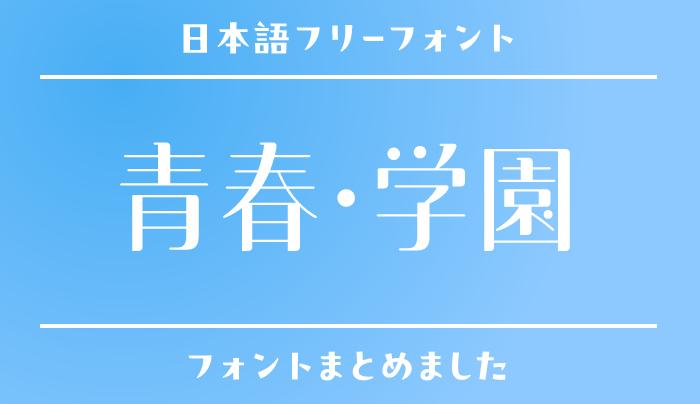
放課後のノート、文化祭のポスター、卒業前に渡す手紙。青春や学園のデザインには、手書きの親密さだけでなく、掲示物らしい明快さや文芸作品らしい静けさも似合います。同じ学校生活でも、どの場面を切り取るかで選びたい文字は変わります。
今回は、フォントラボから青春・学園をテーマに使いたい15書体を紹介します。写真に添える言葉、クラス企画の告知、学校を舞台にした創作まで、具体的な使い道と合わせて選びました。実際の学校名や人名に必要な漢字が入っているかも確認してみてください。
青春・学園を表現する日本語フリーフォント
みかちゃん
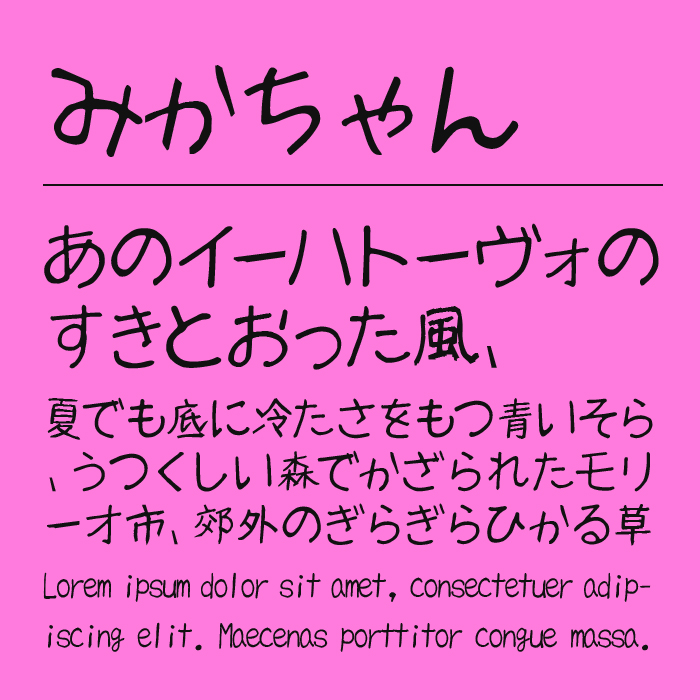
| おすすめの場面 | クラスの思い出写真/寄せ書き風デザイン/卒業記念の一言 |
飾らない筆跡で、友人との距離感を近く。
ほどよく不揃いな文字の大きさや丸みが、友達のノートを読むような親密さを作ります。集合写真に添える一言や、思い出を並べるページにおすすめです。長い案内文まで手書きにせず、話しかけるような言葉だけに使うと効果的。整った本文書体と並べることで、個人の声として見せられます。
ちはや純
| おすすめの場面 | 入学の思い出ページ/素朴な日記風画像/クラス紹介 |
素直な手書きで、少し不器用な気持ちを。
丸みがあり、丁寧に書いたような素朴さを感じる文字です。派手な青春のロゴより、入学した日の記録や初々しい自己紹介などに向いています。余白のある写真に短い感想を添えると、作り込みすぎない表情に。かわいさを装飾で増やすより、言葉を読ませる静かな構成がおすすめです。
きろ字
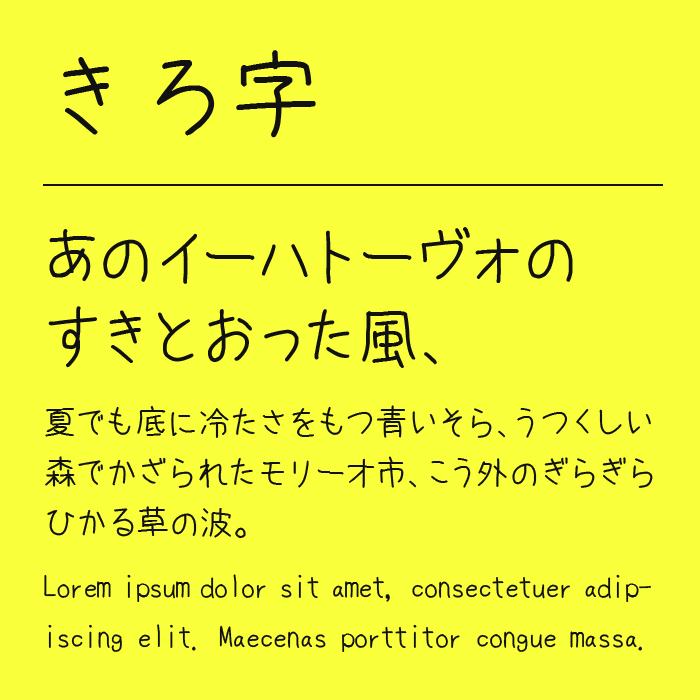
| おすすめの場面 | 文集の短いコメント/部活動の活動記録/交換ノート風レイアウト |
読みやすい手書きで、日常の記録を残す。
手書きらしい温かさを持ちながら、文字の形が落ち着いている書体です。思い出を少し長めに語るコメントや、部活動の記録におすすめ。ラフすぎる文字では読みづらいと感じる場面でも、候補にしやすいバランスです。行間を確保して、文章のかたまりを小さく分けると読み進めやすくなります。
はる手書き
| おすすめの場面 | 卒業前の手紙風コピー/放課後の写真/学園作品のモノローグ |
細い筆跡で、言い切れない余韻を残す。
ノートに書き留めたような細い線が、静かな感情を伝えます。にぎやかな告知より、夕方の教室や帰り道の写真に添える短い言葉と好相性。文章の周りに空間を残すと、控えめな筆跡が活きます。線が細いため、写真に重ねる際は背景との明暗差を確保してください。
ぱぱっとメモ
| おすすめの場面 | ノートの走り書き/学園作品の小道具/部室のメモ風画像 |
整いすぎない文字で、学校生活の一瞬を。
走り書きのような線の揺れが、急いで残したメモの雰囲気を作ります。画面の中心のタイトルより、ノートの片隅や部室の貼り紙にある一言におすすめ。無料のバージョン1は漢字なしなので、かなのメッセージや英数字の予定表示を中心に使うと自然です。漢字を混ぜる場合は見た目の差にも注意しましょう。
まちのてちょう
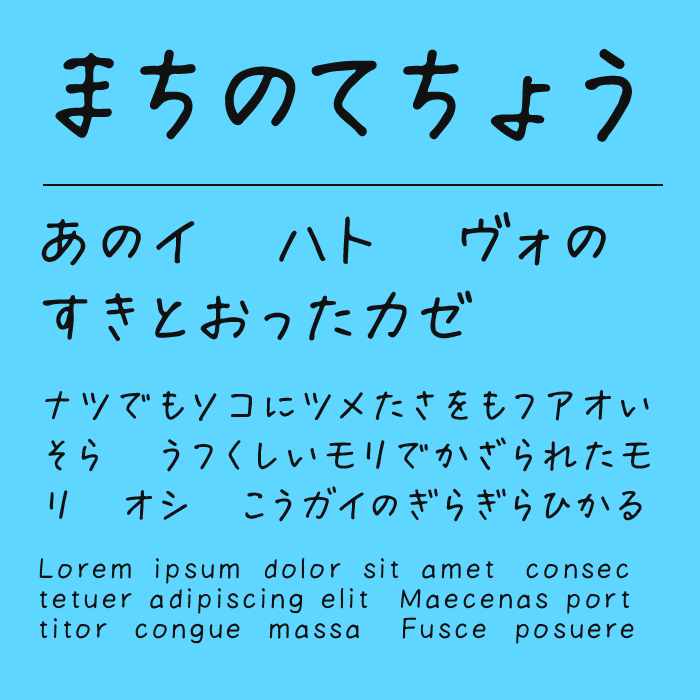
| おすすめの場面 | 文化祭の手描き案内/通学路のマップ/学校生活の小冊子 |
暮らしに近い手書きで、学校の周辺まで描く。
墨だまりのような表情があり、日常の手帳を思わせる親しみやすさが魅力です。校内だけでなく、通学路のお店や思い出の場所を紹介するマップにも合います。無料版は漢字なしのため、かなで作る短いラベル向け。学校名などの正式な情報には、漢字を収録した別書体を使い分けましょう。
あるぺん
| おすすめの場面 | 卒業アルバムの添え文/部活ノート風デザイン/青春短編の扉 |
ペンのかすれで、記録した時間を感じさせる。
筆圧の揺れやかすれがあり、紙に書いた文字の質感を出したいときに向いています。写真と短いコメントを組み合わせるページや、部活動のノートを思わせる構成におすすめ。無料版の漢字は教育漢字なので、人名や難しい熟語は事前に確認が必要です。商用利用は可能ですが、制作物の商標登録は認められていません。
ぼくたちのゴシック
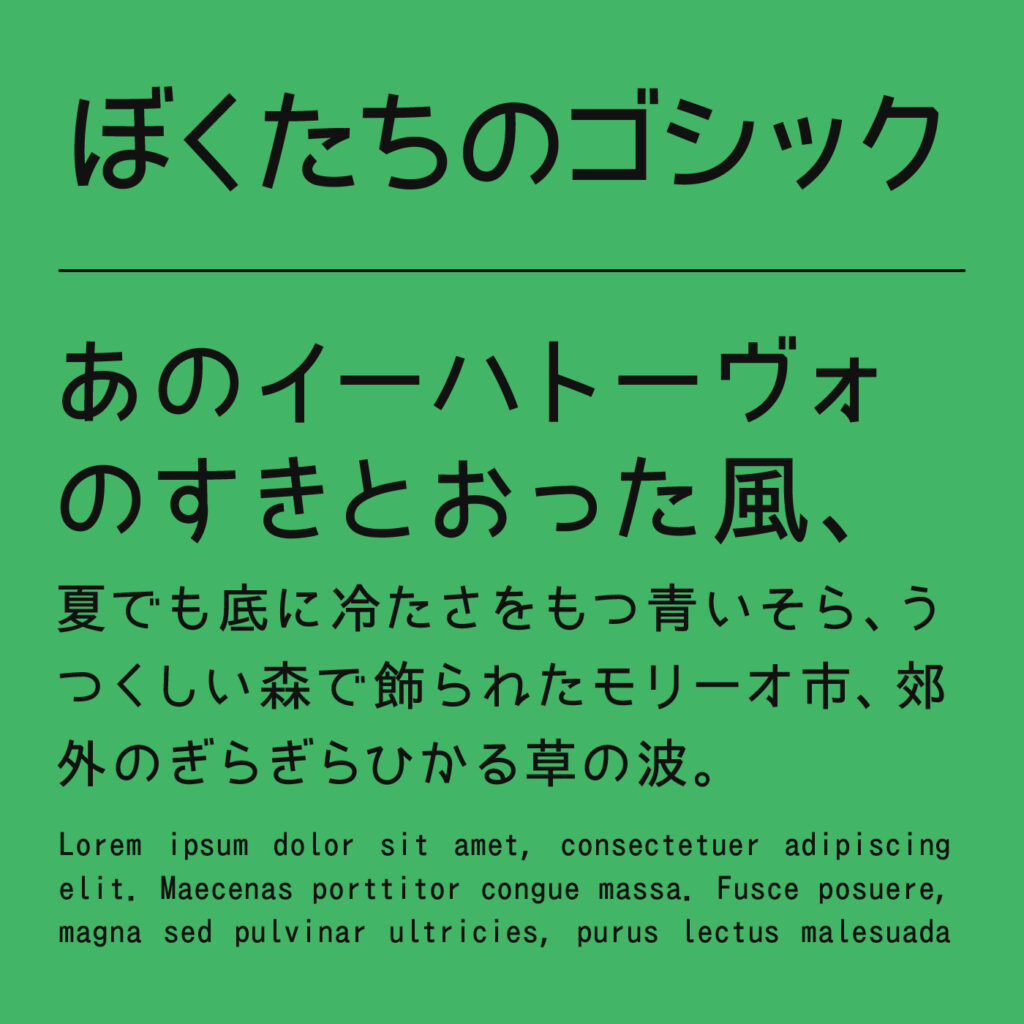
| おすすめの場面 | 学校行事の案内/クラス紹介/生徒向けの配布物 |
ほどよくやわらかいゴシックで、情報を親しみやすく。
かなのやさしい表情が、学校からのお知らせを堅苦しく見せたくないときに役立ちます。青春の雰囲気を強く飾るより、日付や場所をきちんと届ける役割におすすめ。手書きタイトルの下に説明を添える組み合わせも使いやすく、ページ全体を落ち着かせながら親近感を残せます。
モボ
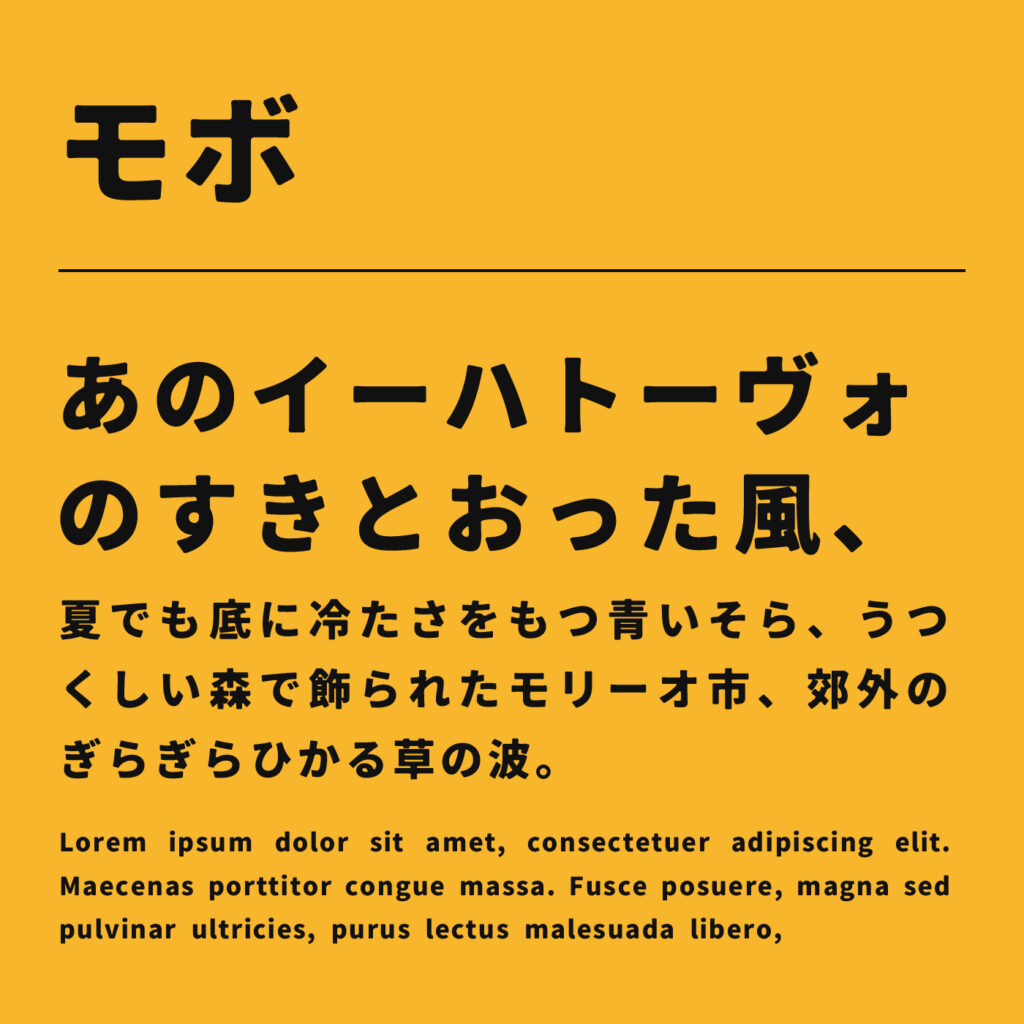
| おすすめの場面 | 文化祭パンフレット/部活動の紹介/卒業記念冊子 |
角丸のゴシックで、今の学校生活を軽やかに。
角ゴシックの骨格に丸みがあり、まじめさと親しみやすさのバランスを取れます。見出しと本文で太さを変え、冊子全体を揃えたいときにおすすめ。手書きほど私的ではなく、一般的な案内文ほど硬くもない印象にできます。太いスタイルは短い見出し、標準的な太さは説明文へと役割を分けましょう。
LINE Seed JP
| おすすめの場面 | オープンキャンパス案内/新入生向け資料/学園イベントの告知 |
明快な文字で、初めての場所への不安を減らす。
親しみのある角丸ゴシックが、新入生や来場者に情報を伝えるデザインに向いています。学園もののタイトル演出というより、受付場所や参加方法を見つけやすく整えるための候補。複数の太さを使い、見出しと本文の差を作れます。色だけに頼らず情報を整理したいときにもおすすめです。
いろは角クラシック
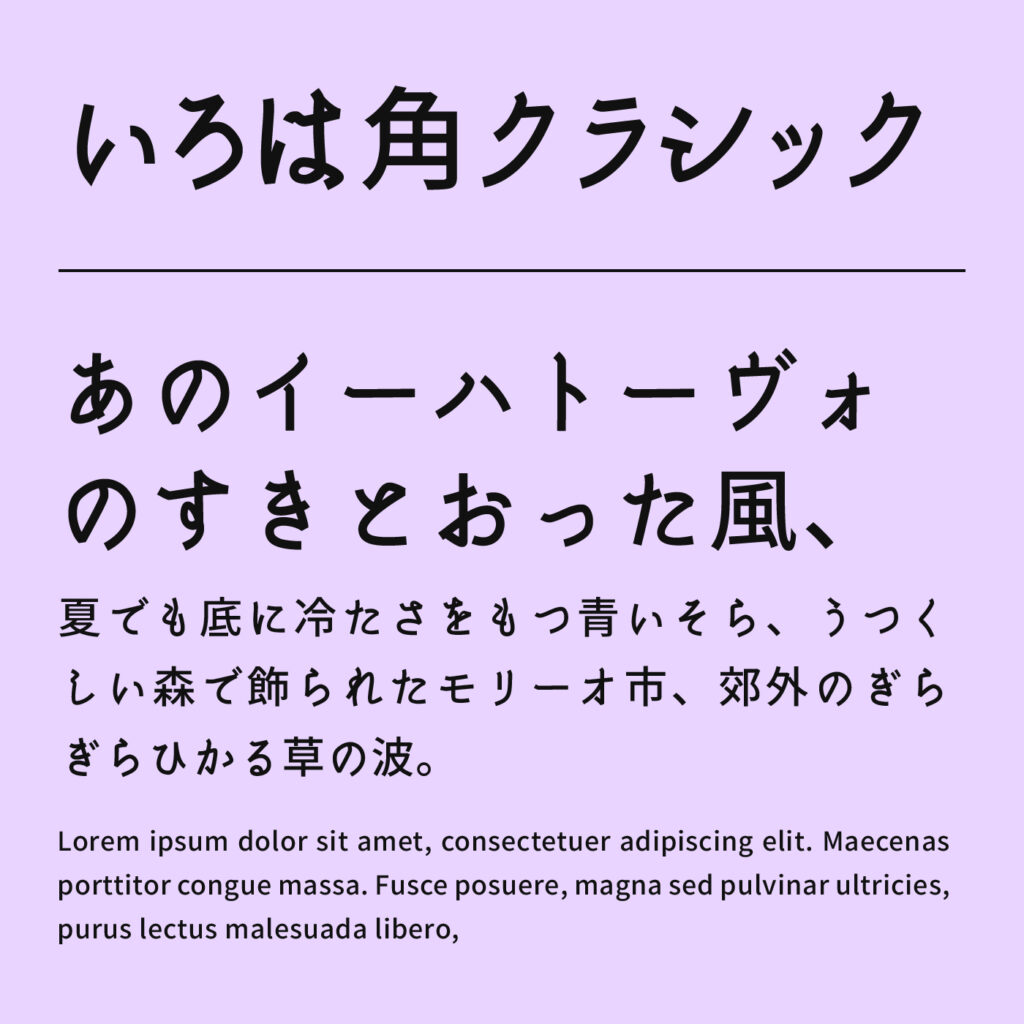
| おすすめの場面 | 文芸部の冊子/学園小説の章見出し/図書室の掲示 |
古風なかなで、少し文学的な学園へ。
はねやはらいに古典的なニュアンスがあり、一般的な角ゴシックより物語を感じる書体です。文芸部の作品集や図書室の企画など、学校生活の静かな側面を表現したいときにおすすめ。古い校舎の写真とも合わせやすく、懐かしさをやりすぎずに添えられます。
Noto Sans
| おすすめの場面 | 行事の日時・会場案内/学校紹介の本文/文化祭のプログラム |
演出を支える、読みやすい情報用の文字。
日本語対応のNoto Sans JPなどを選び、必要な情報を素直に届ける役割に使います。写真や手書きのコピーが主役のページほど、本文は安定した書体で支えると整理しやすくなります。会場名、時間割、持ち物などを明快に見せたい場面におすすめ。世界観を足す書体ではなく、読み手を迷わせないための選択です。
Rounded M+
| おすすめの場面 | 新入生歓迎の案内/クラス企画の説明/学園イベントのマップ |
丸い角で、声をかけやすい雰囲気に。
M+をもとに角を丸めた書体で、案内をやさしく見せたいときに向いています。丸さの違いを選べるため、幼く見せたくない場合は控えめなタイプから試すのがおすすめ。企画名は大きく、説明文は標準的な太さにすると、親しみやすさと情報の読み取りやすさを両立できます。
源暎Nuゴシック
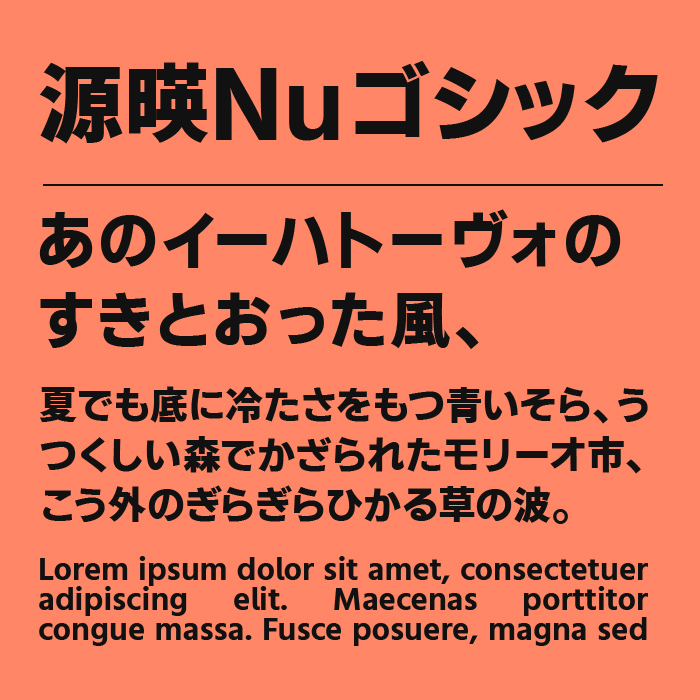
| おすすめの場面 | 文化祭の企画名/部活動の募集見出し/体育祭の短いスローガン |
太い文字で、学校行事の熱量を伝える。
しっかりした太さがありながら、角にやわらかさが残るゴシック体です。掲示物でまず読んでほしい企画名や、短い呼びかけにおすすめ。細い手書きの一言と組み合わせると、勢いと個人の声を分けて表現できます。詳細な日時や長い注意文まで太くせず、主役の言葉に絞ると見やすくなります。
源暎こぶり明朝
| おすすめの場面 | 卒業文集/学園小説の本文/青春エッセイ |
思い出の文章を、落ち着いて読ませる明朝。
こぶりなかなが文章にリズムを作り、長文を落ち着いて読ませたい場面に向いています。にぎやかな青春だけでなく、振り返る時間や静かな語りを扱う作品におすすめ。タイトルは手書き、本文はこちらの明朝という使い分けも可能です。文集では名前や旧字体が表示できるか、組版前に確認しましょう。